Trong thế giới thiết kế số hiện đại, việc lựa chọn Font Unicode Đẹp không chỉ là vấn đề thẩm mỹ mà còn là yếu tố then chốt đảm bảo khả năng hiển thị và tương thích trên mọi nền tảng. Bài viết này, thuộc chuyên mục Blog, sẽ đi sâu vào tầm quan trọng của Font Unicode trong thiết kế Việt, phân tích các tiêu chí lựa chọn font chữ đẹp, phù hợp với từng dự án cụ thể. Chúng tôi sẽ giới thiệu top các font tiếng Việt Unicode được ưa chuộng nhất năm 2025, đồng thời hướng dẫn bạn cách tải font Unicode miễn phí và cài đặt font chữ một cách dễ dàng. Bên cạnh đó, bài viết cũng đề cập đến vấn đề lỗi font chữ thường gặp và các giải pháp khắc phục hiệu quả, giúp bạn tối ưu hóa trải nghiệm thiết kế và đảm bảo sự chuyên nghiệp cho sản phẩm của mình.
Font Unicode Đẹp: Giải Pháp Hoàn Hảo Cho Thiết Kế Việt 2025 – Tải Ngay!
Font Unicode Đẹp: Tại Sao Thiết Kế Việt Cần Đến Chúng?
Font Unicode đẹp không chỉ là một yếu tố thẩm mỹ mà còn là giải pháp hoàn hảo cho thiết kế Việt, đảm bảo khả năng hiển thị chính xác và nhất quán trên mọi nền tảng. Việc sử dụng font Unicode giúp tránh tình trạng lỗi font, hiển thị sai ký tự tiếng Việt, đặc biệt quan trọng trong bối cảnh hội nhập quốc tế và sự phát triển mạnh mẽ của các nền tảng số. Điều này giúp thương hiệu xây dựng hình ảnh chuyên nghiệp và đáng tin cậy hơn.
Sự cần thiết của font Unicode trong thiết kế Việt Nam xuất phát từ khả năng tương thích vượt trội. Các font chữ theo chuẩn Unicode, trái ngược với các bảng mã cũ như VNI hay ABC, đảm bảo văn bản tiếng Việt hiển thị chính xác trên mọi hệ điều hành, trình duyệt web và thiết bị di động. Điều này đặc biệt quan trọng trong thời đại mà người dùng truy cập thông tin từ nhiều nguồn khác nhau, sử dụng đa dạng thiết bị. Một thiết kế sử dụng font không chuẩn Unicode có nguy cơ hiển thị lỗi trên một số thiết bị, gây ảnh hưởng tiêu cực đến trải nghiệm người dùng và uy tín của thương hiệu.
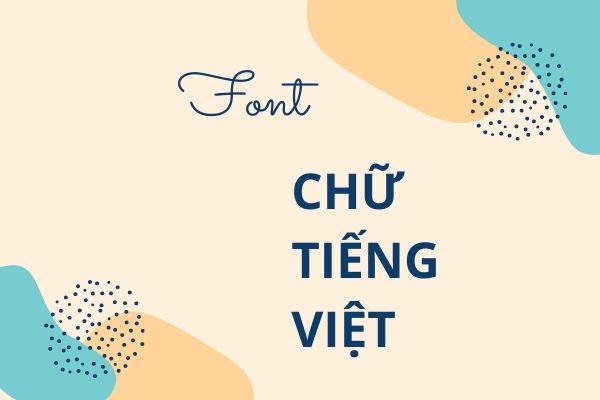
Việc sử dụng font Unicode đẹp còn mang lại nhiều lợi ích thiết thực:
- Tính thẩm mỹ: Font Unicode ngày càng đa dạng về kiểu dáng, từ cổ điển đến hiện đại, đáp ứng nhu cầu sáng tạo của các nhà thiết kế.
- Khả năng đọc: Các font Unicode được thiết kế tỉ mỉ, đảm bảo khả năng đọc tốt trên cả màn hình và bản in.
- Tiết kiệm thời gian và chi phí: Sử dụng font Unicode giúp tránh các vấn đề liên quan đến lỗi font, giảm thiểu thời gian chỉnh sửa và đảm bảo tính nhất quán của thiết kế.
- Tối ưu SEO: Các trang web sử dụng font Unicode thân thiện hơn với các công cụ tìm kiếm, giúp cải thiện thứ hạng trên Google và thu hút nhiều khách hàng tiềm năng.
Ngoài ra, font Unicode đóng vai trò quan trọng trong việc bảo tồn và phát huy bản sắc văn hóa Việt Nam. Việc sử dụng các font chữ mang đậm dấu ấn Việt không chỉ giúp tạo ra những thiết kế độc đáo mà còn góp phần quảng bá văn hóa Việt ra thế giới.
Khám Phá Kho Font Unicode Tiếng Việt Đẹp Mắt & Miễn Phí Năm 2025
Năm 2025 hứa hẹn mang đến một thế giới font Unicode tiếng Việt đa dạng và phong phú, mở ra vô vàn cơ hội sáng tạo cho thiết kế Việt; việc tìm kiếm và sử dụng font Unicode đẹp đã trở nên dễ dàng hơn bao giờ hết. Sự phát triển mạnh mẽ của cộng đồng thiết kế và các nhà phát triển font đã tạo ra một kho tàng font khổng lồ, đáp ứng mọi nhu cầu từ thiết kế logo, branding, UX/UI design đến ấn phẩm in ấn.
Vậy, đâu là những nguồn cung cấp font Unicode tiếng Việt miễn phí đáng tin cậy, và làm thế nào để tìm kiếm được những font phù hợp với dự án của bạn?
- Google Fonts: Là một thư viện font trực tuyến miễn phí khổng lồ của Google, cung cấp hàng trăm font Unicode hỗ trợ tiếng Việt. Điểm mạnh của Google Fonts là tính ổn định, dễ sử dụng và khả năng tích hợp trực tiếp vào website. Một số font phổ biến được yêu thích như Roboto, Open Sans, Montserrat đã được Việt hóa.
- Fontshare: Nền tảng font miễn phí từ Indian Type Foundry, cung cấp các font chất lượng cao, được thiết kế tỉ mỉ và có tính thẩm mỹ cao. Fontshare chú trọng vào việc cung cấp font cho thiết kế chuyên nghiệp, với nhiều lựa chọn font độc đáo và sáng tạo.
- Các trang web chia sẻ font miễn phí: Bên cạnh các nguồn chính thức, có rất nhiều trang web chia sẻ font miễn phí khác. Tuy nhiên, cần cẩn trọng khi tải font từ các nguồn này để tránh các vấn đề về bản quyền và virus. Một số trang web uy tín có thể kể đến như Font Squirrel, DaFont, và Behance.
Để tìm kiếm font Unicode tiếng Việt hiệu quả, hãy lưu ý một vài điểm sau:
- Xác định rõ mục đích sử dụng: Bạn cần font cho logo, website, hay ấn phẩm in ấn? Mỗi mục đích sử dụng sẽ phù hợp với một loại font khác nhau.
- Lựa chọn font phù hợp với phong cách thiết kế: Font phải hài hòa với tổng thể thiết kế, thể hiện được thông điệp và cá tính của thương hiệu.
- Kiểm tra kỹ lưỡng khả năng hiển thị tiếng Việt: Đảm bảo font hỗ trợ đầy đủ các ký tự tiếng Việt có dấu để tránh lỗi hiển thị.
- Đọc kỹ điều khoản sử dụng: Chú ý đến các quy định về bản quyền, đặc biệt nếu bạn sử dụng font cho mục đích thương mại.
Với sự phát triển không ngừng của công nghệ và sự sáng tạo của cộng đồng thiết kế, kho font Unicode tiếng Việt đẹp mắt và miễn phí năm 2025 sẽ tiếp tục được mở rộng và nâng cao về chất lượng. Việc khám phá và lựa chọn font phù hợp sẽ giúp bạn tạo ra những thiết kế ấn tượng và chuyên nghiệp, góp phần khẳng định bản sắc văn hóa Việt Nam trên thị trường quốc tế.
Để hiện thực hóa những ý tưởng này, các nhà thiết kế có thể sử dụng các phần mềm thiết kế font chuyên nghiệp như Glyphs, FontLab Studio, hay RoboFont. Đồng thời, việc nghiên cứu kỹ lưỡng về lịch sử, văn hóa Việt Nam là vô cùng quan trọng để đảm bảo tính chính xác và thẩm mỹ cho sản phẩm. Quan trọng hơn, cần ý thức về bản quyền font Unicode và tìm hiểu kỹ lưỡng các quy định pháp luật liên quan trước khi sử dụng hoặc phân phối các font chữ được tạo ra.